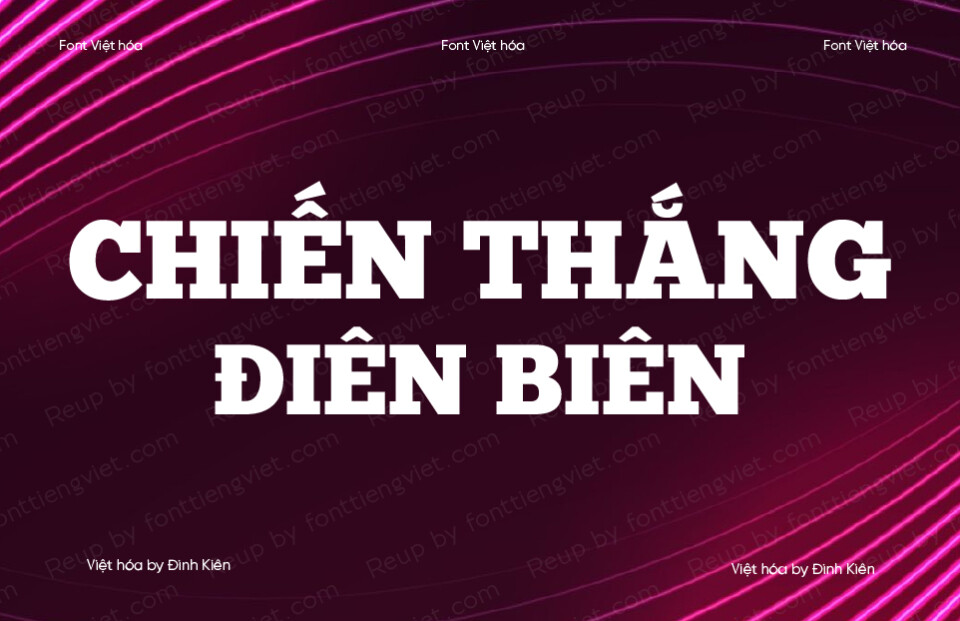
Tải Font Việt hóa UTM ChunkFive: Sự Lựa Chọn Hoàn Hảo Cho Thiết Kế Ấn Tượng
Trong thế giới thiết kế đồ họa đầy cạnh tranh, việc lựa chọn một Font Chữ chất lượng là yếu tố then chốt quyết định sự thành công của một dự án. Đặc biệt đối với học sinh, sinh viên và các nhà thiết kế trẻ thường xuyên tạo ra các ấn phẩm truyền thông cho trường học hoặc các bài tập lớn, nhu cầu về một phông chữ mạnh mẽ, dễ đọc và đã được Việt hóa là vô cùng cấp thiết. Hôm nay, chúng ta sẽ đi sâu vào tìm hiểu về một lựa chọn tuyệt vời đã trở nên quen thuộc trong cộng đồng thiết kế Việt Nam: Font Việt hóa UTM ChunkFive.
ChunkFive là một phông chữ slab serif retro nổi tiếng, được biết đến với vẻ ngoài đậm, chắc chắn và khả năng tạo ra sự chú ý ngay lập tức. Tuy nhiên, để sử dụng hiệu quả trong các tài liệu tiếng Việt, phiên bản Việt hóa là điều không thể thiếu. Phiên bản Font Việt hóa UTM ChunkFive đã giải quyết hoàn toàn vấn đề này, đảm bảo các ký tự tiếng Việt, dấu thanh, và khoảng cách được hiển thị một cách hoàn hảo, giữ nguyên tinh thần thiết kế ban đầu.
Font Việt hóa UTM ChunkFive: Đặc Điểm Nổi Bật và Lịch Sử Phát Triển
ChunkFive ban đầu được thiết kế bởi Meredith Mandel, lấy cảm hứng từ những phông chữ quảng cáo cổ điển của thế kỷ 19. Nó thuộc nhóm slab serif, tức là các nét chân (serif) rất dày và vuông vức, tạo cảm giác vững chãi và cổ điển mạnh mẽ (retro). Nhờ đặc tính này, nó thường được gọi là “font chữ khối” hay “font impact”.
Điểm mạnh nhất của Font Việt hóa UTM ChunkFive chính là sự bùng nổ về mặt thị giác. Nó có trọng lượng cực kỳ nặng (Ultra-bold), khiến nó nổi bật ngay cả khi được sử dụng ở kích thước nhỏ. Sự Việt hóa bởi nhóm UTM không chỉ thêm vào các ký tự ă, â, đ, ê, ô, ư mà còn tinh chỉnh kerning (khoảng cách giữa các ký tự) và hinting để đảm bảo font hiển thị sắc nét trên mọi màn hình và khi in ấn. Điều này cực kỳ quan trọng đối với các ấn phẩm học đường hoặc tài liệu thi cử cần sự rõ ràng tối đa.
Ứng Dụng Đa Dạng Của Font Chữ UTM ChunkFive Trong Học Tập và Thiết Kế
Mặc dù có vẻ ngoài cổ điển, phông chữ này lại có ứng dụng rất hiện đại và linh hoạt. Sinh viên và học sinh cấp 3 có thể sử dụng Font Việt hóa UTM ChunkFive trong nhiều dự án khác nhau, từ thiết kế bìa sách, báo cáo chuyên đề, đến các ấn phẩm phục vụ sự kiện của trường. Đặc biệt, nó rất phù hợp cho các tiêu đề lớn trong tài liệu ôn tập và đề thi thử tốt nghiệp, giúp các thông tin quan trọng được nhấn mạnh một cách hiệu quả.
Thiết Kế Poster, Banner và Đồ Họa Quảng Cáo
Trong lĩnh vực thiết kế đồ họa, ChunkFive là “vũ khí” tuyệt vời cho các tiêu đề lớn, cần sự thu hút cao. Nếu bạn đang thiết kế poster quảng bá cho buổi thi thử tốt nghiệp, hay một banner chào mừng năm học mới, sự mạnh mẽ của font này sẽ giúp thông điệp của bạn được truyền tải một cách dứt khoát và đầy năng lượng. Đây là một phông chữ giúp tạo ra sự tương phản ấn tượng so với các phông chữ nội dung (body text) mảnh mai hơn, thường dùng cho các tài liệu dài.
Các nhà thiết kế typography đánh giá cao sự cân bằng giữa tính cổ điển và hiện đại mà ChunkFive mang lại. Nó không chỉ đơn thuần là một font chữ đậm, mà còn chứa đựng một câu chuyện về phong cách thiết kế retro. Việc kết hợp nó với các yếu tố hình ảnh liên quan đến trường học, như sách vở, bút chì, hay biểu tượng học sinh, sẽ tạo nên những tác phẩm vừa chuyên nghiệp vừa gần gũi. Ngoài ra, việc sử dụng phông chữ slab serif chất lượng cao như UTM ChunkFive cũng góp phần nâng cao tính thẩm mỹ và sự chuyên nghiệp của các ấn phẩm truyền thông đa phương tiện.
Lựa Chọn Tối Ưu Cho Tiêu Đề Bài Giảng và Slide Thuyết Trình
Đối với giáo viên và giảng viên, việc chuẩn bị tài liệu trực quan là vô cùng quan trọng. Font Việt hóa UTM ChunkFive cung cấp độ đọc hiểu cao (legibility) ngay cả khi trình chiếu ở khoảng cách xa. Kích thước và độ đậm của nó giúp tiêu đề slide thuyết trình PowerPoint trở nên rõ ràng, không bị chìm lẫn, hỗ trợ đắc lực trong việc truyền đạt kiến thức một cách mạch lạc và ấn tượng.
Tóm lại, Font Việt hóa UTM ChunkFive không chỉ là một phông chữ đẹp mà còn là một công cụ mạnh mẽ giúp nâng cao chất lượng các ấn phẩm truyền thông của bạn, từ bài thuyết trình học thuật đến các thiết kế quảng cáo chuyên nghiệp. Với khả năng hỗ trợ tiếng Việt hoàn hảo và phong cách thiết kế không thể nhầm lẫn, nó xứng đáng có mặt trong bộ sưu tập typography của mọi người làm thiết kế. Đừng ngần ngại tải về và trải nghiệm sức mạnh của dòng Font Chữ ấn tượng này ngay hôm nay để tạo ra những tác phẩm thực sự nổi bật trong mắt giám khảo hoặc khán giả của bạn.